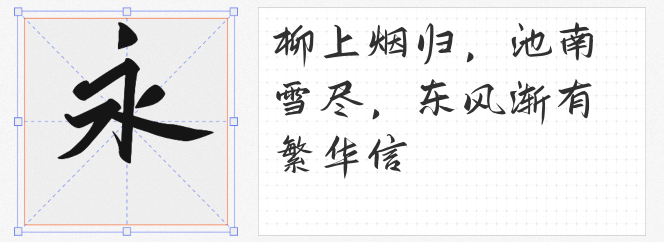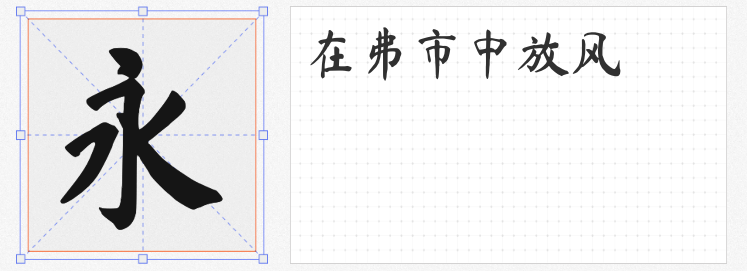
传统笔意与现代设计的碰撞☆四款免费商用中国潮手写书法字体推荐
在国潮设计蔚然成风的今天,兼具文化底蕴与视觉张力的手写书法字体成为设计师的“刚需”。本文精选四款免费商用字体,涵盖磅礴对联体、清秀小楷、刚柔并济的现代书法与手写匠心之作,助力传统美学与商业设计的融合创新。
1.马善政毛笔楷书
源自谷歌开源字体项目的马善政毛笔楷书,以传统对联字体为灵感,笔触浑厚如磐石,飞白处见筋骨,字形间洋溢着庙堂之上的庄严感。其笔画粗细对比强烈,转折处如刀刻斧凿,尤其适合春节贺卡、寺庙楹联或武侠风海报标题。作为开源字体,它打破了商用书法字体高昂的授权门槛,让传统对联的恢弘气韵触手可及。
2.演示悠然小楷
“演示悠然小楷”以明代小楷为基,化繁为简,摒弃过度连笔与飞白,保留了楷书“横平竖直”的端庄骨架。其字形紧凑而不拥挤,天然适配长段落排版,即便作为书籍内文或产品说明也毫无阅读压力。淡雅的笔触间透着文人书卷气,是国潮品牌故事页、中式点心包装文案的理想之选。
3.有字库龙藏体
以书法家陈晓敏手稿为蓝本的龙藏体,堪称传统笔意与现代审美的平衡典范。笔画粗细适中,横画如铁画银钩,竖画似松柏挺立,既有魏碑的刚劲,又含行书的灵动。这款字体在品牌LOGO、茶文化海报或国风游戏标题中表现惊艳,既能传递东方哲学的沉稳,又不失当代设计的简洁利落。
4.鸿雷板书简体
由设计师鸿雷手绘板逐字创作的板书简体,保留了纸质书写的自然肌理。笔画粗细随运笔起伏,捺画如长袖舒展,点画似坠石有声,仿佛能触摸到创作者落笔时的呼吸节奏。这款字体极适合儿童教育品牌、手作店铺招牌或文艺风明信片,其手写温度能瞬间拉近与观者的情感距离。